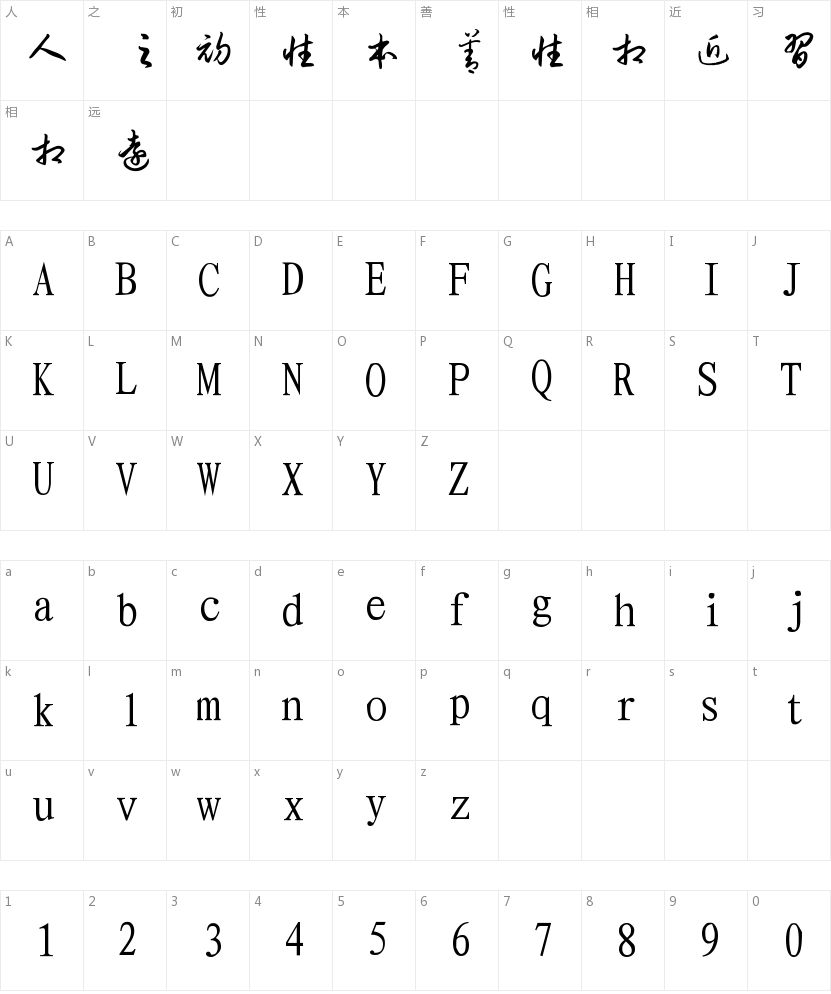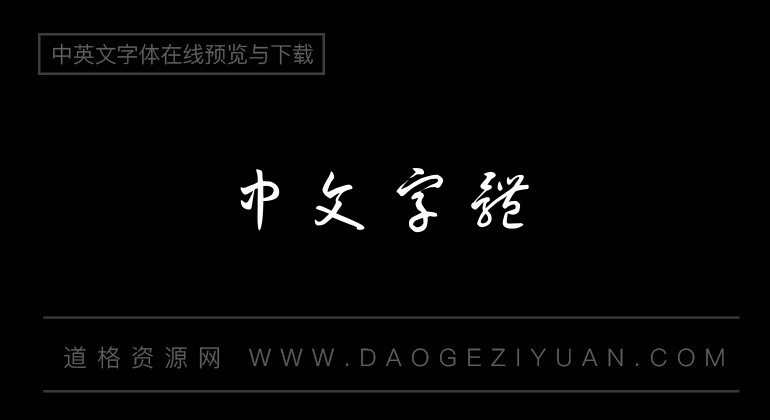
博洋草书3500是一款草书字体,由博洋设计师林洋设计,由博洋字体工作室出品。它是一款精致的草书字体,具有精细的笔画,细腻的线条,清晰的结构,圆润的曲线,优雅的风格,以及良好的空间感。它的特点是笔画流畅,笔画细腻,空间感强,字体质感自然,字形结构清晰,适用于各种类型的书法字体设计,是一款优秀的草书字体。文件名:BoYangCaoShu3500-1.ttf
博洋草书3500是一款非常不错的手写艺术字体,具有很好的视觉感,适合于文化类的宣传设计、商业类品牌的广告和产品包装设计以及个性化文字排版等较多场景。